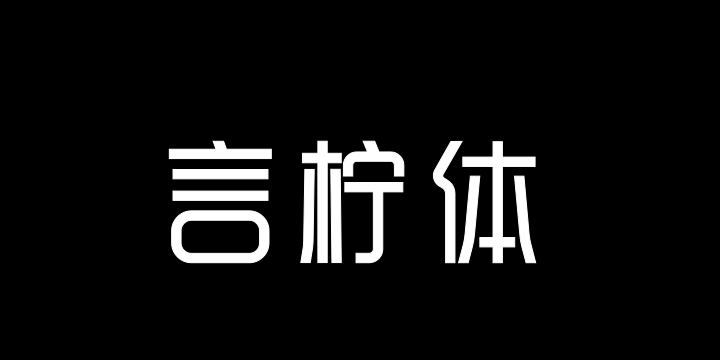
孟祥朝言柠体 By 孟祥朝字体 商用字体
字体全名: 孟祥朝言柠体
铸字厂: 孟祥朝字体
设计师: 孟祥朝
字体简介: 《孟祥朝言柠体》是由孟祥朝独立创作的字体美术作品,历经三年打磨完成;整套字体一共收录了7121个汉字,搭配245个常用字符,实用性拉满。这7121个汉字里,不仅完整涵盖了GB2312标准里的6763个基础常用字,还额外补充了不少咱们日常生活里高频用到的生僻字、俗语用字。该字体是以时尚简约的风格来设计,线条细腻柔和、笔触利落清爽,看着干净雅致,没有冗余的装饰,字形疏朗均衡;长时间阅读也不会觉得累。它的适用场景特别广,如做广告海报、品牌用字、产品包装、书刊排版这些商业设计,它都能轻松驾驭,就连公众号推文、短视频字幕、网页设计、自媒体封面这些新媒体内容,用它排版也格外适配,算是兼顾了颜值和实用性,希望大家能用得舒心、喜欢。